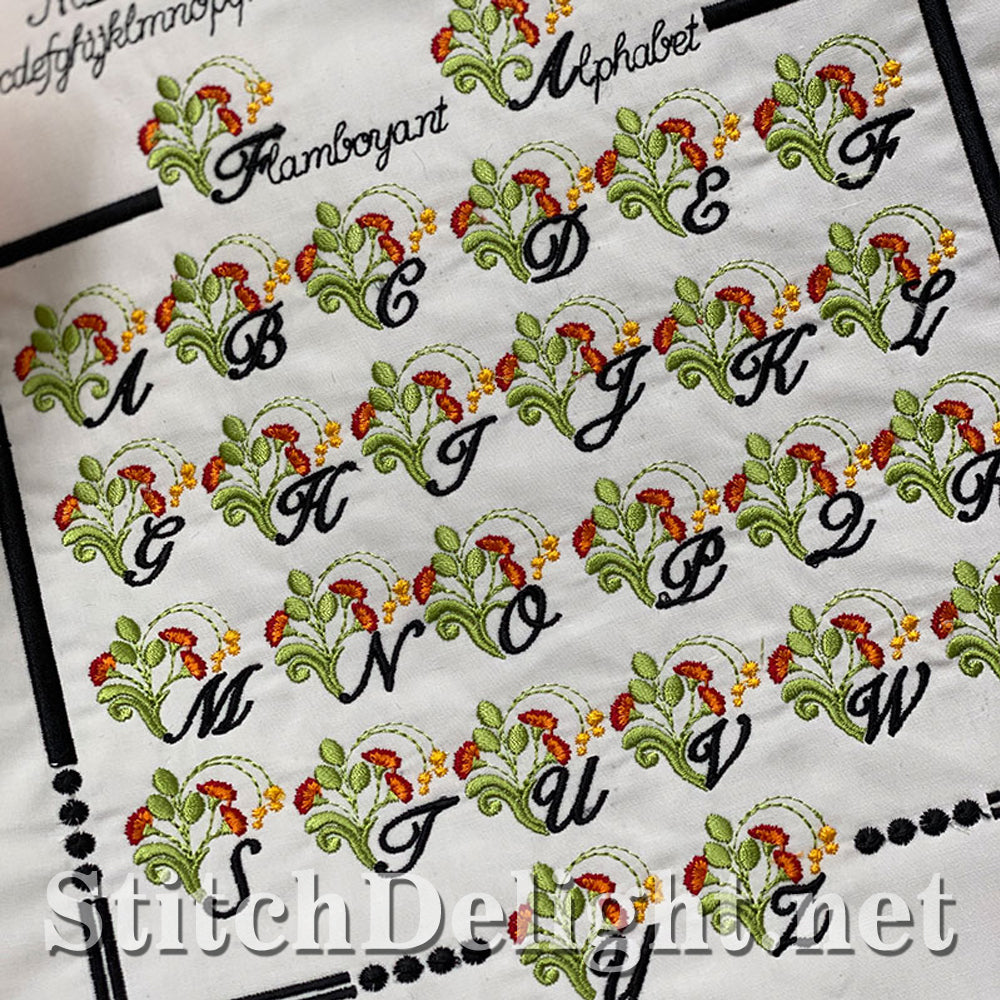
Une petite police d'un peu plus de 1 pouce de hauteur, parfaite pour les petits projets ou les textes plus longs. La police de coordination est SDS1750 qui mesure moins d'un demi-pouce.